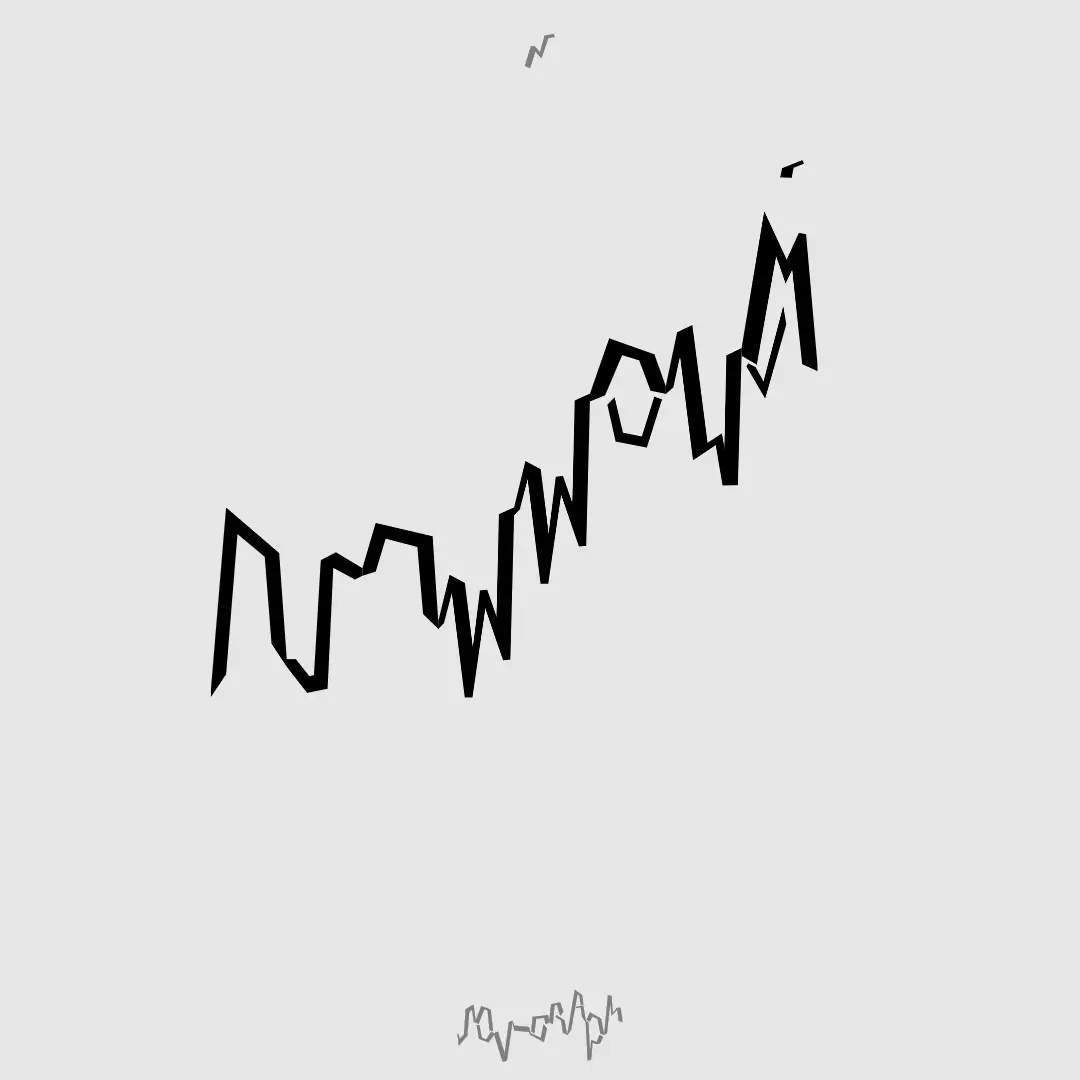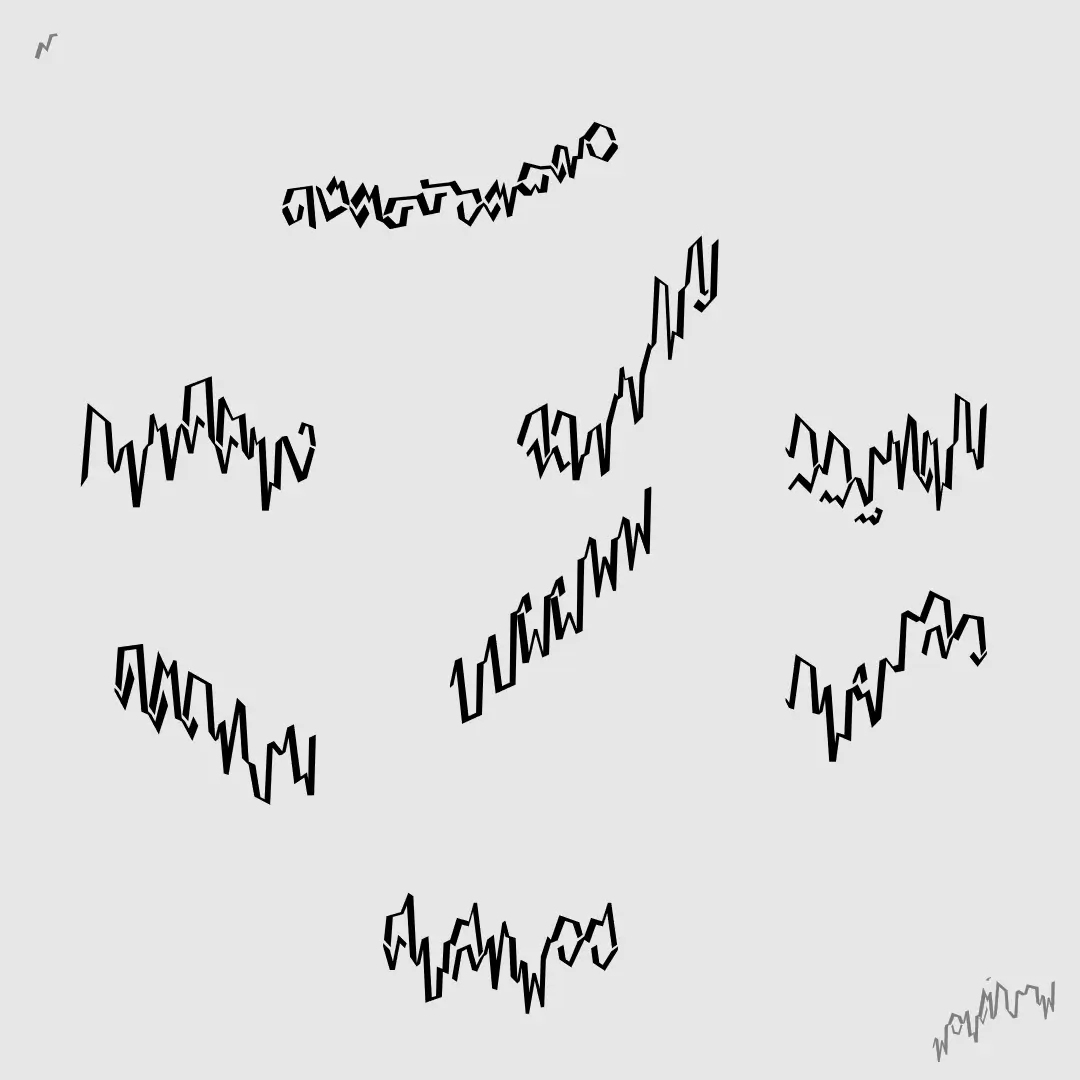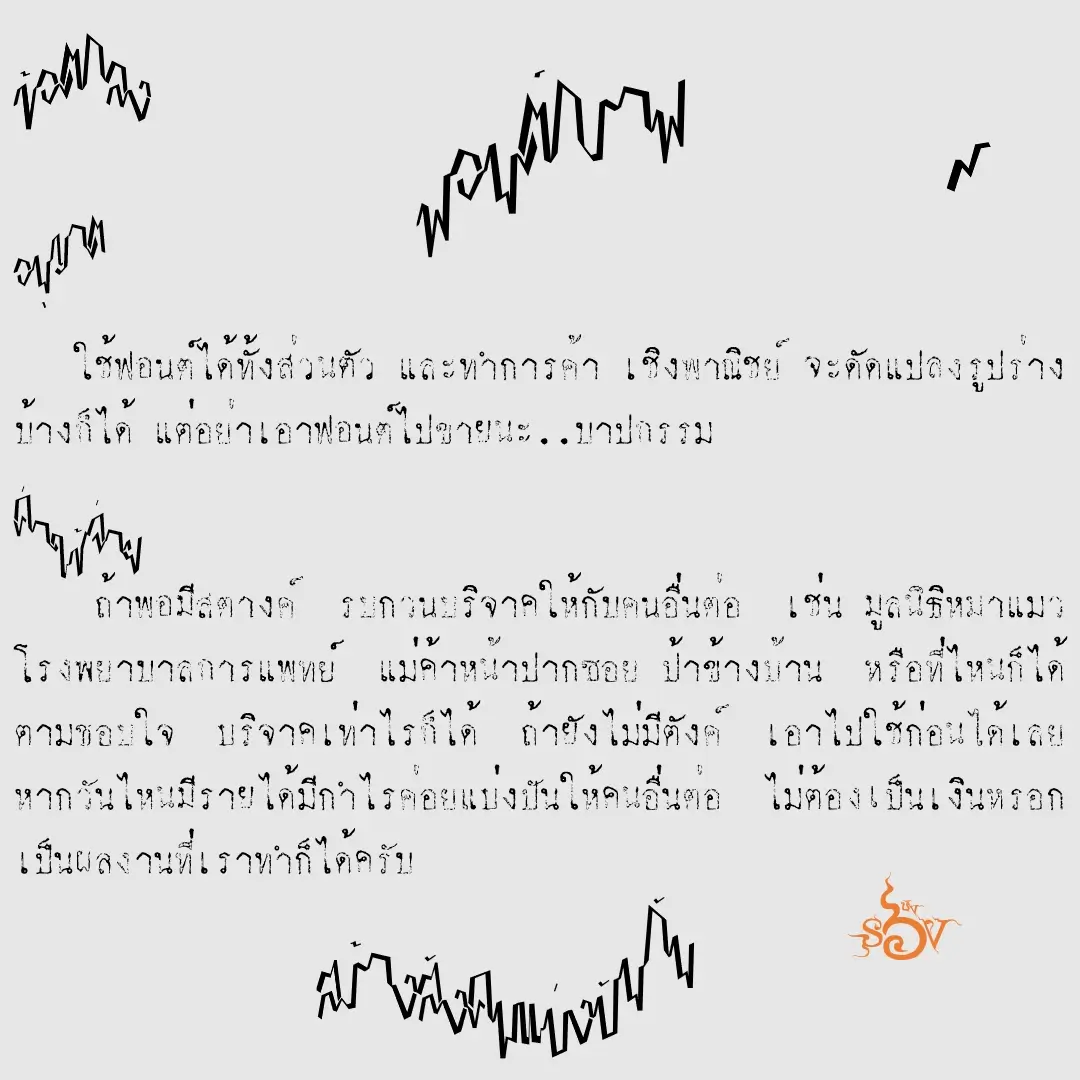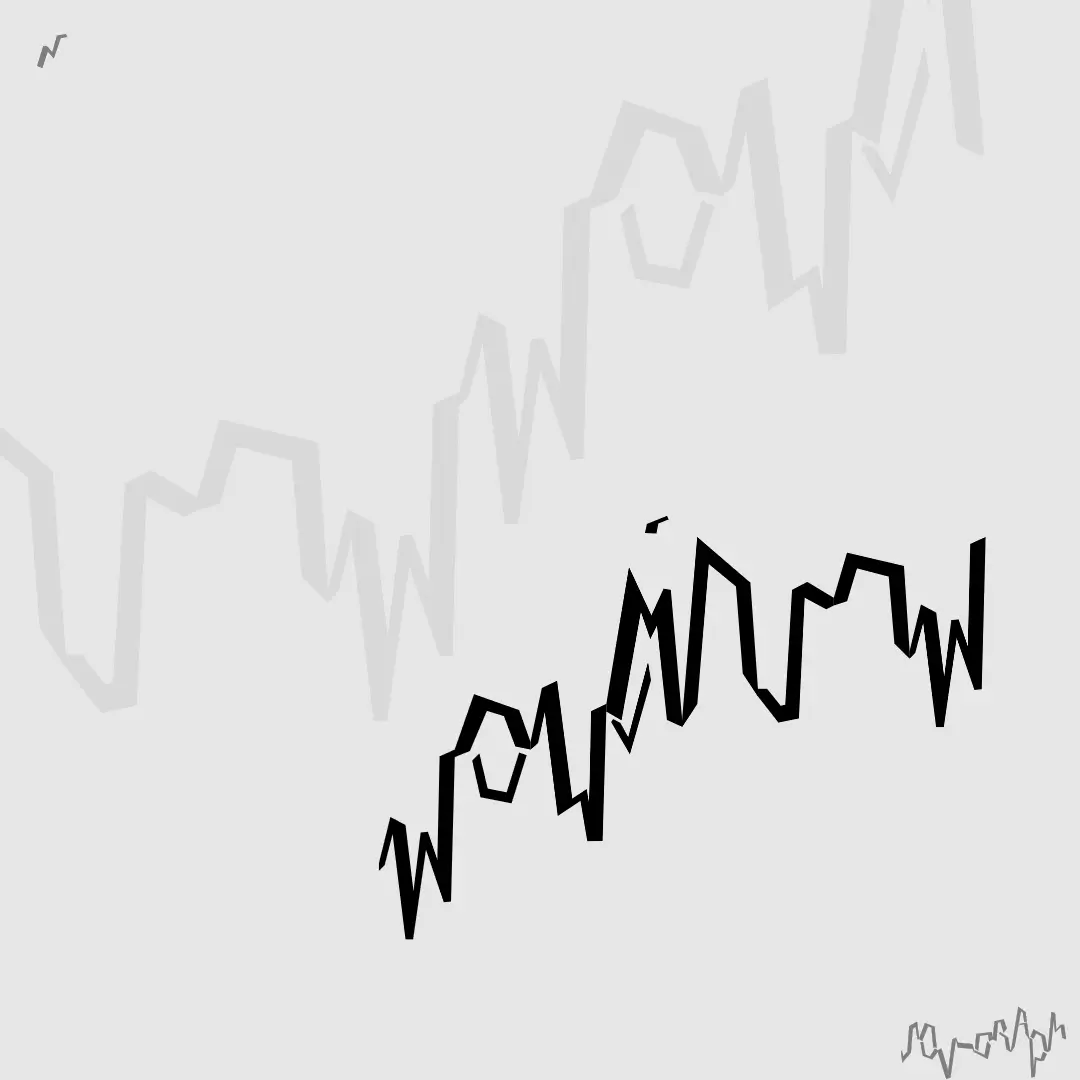
กราฟ – ฟอนต์แบบเส้นกราฟวิ่งขึ้นลง ไม่ถูกจำกัดอยู่ในบรรทัดเดียวแบบฟอนต์ปรกติ แต่นั่นก็สร้างปัญหา… จึงเป็นแค่พาดหัว
เส้นกราฟมี 2 แบบ
- แบบปรกติ เส้นยาวต่อเนื่อง อ่านยากนิดนึง
- กด bold แบบเส้นสั้นกว่า อ่านง่ายกว่านิดนึง แต่ความเป็นกราฟเส้นลดลง
กราฟ (SOV_graph)